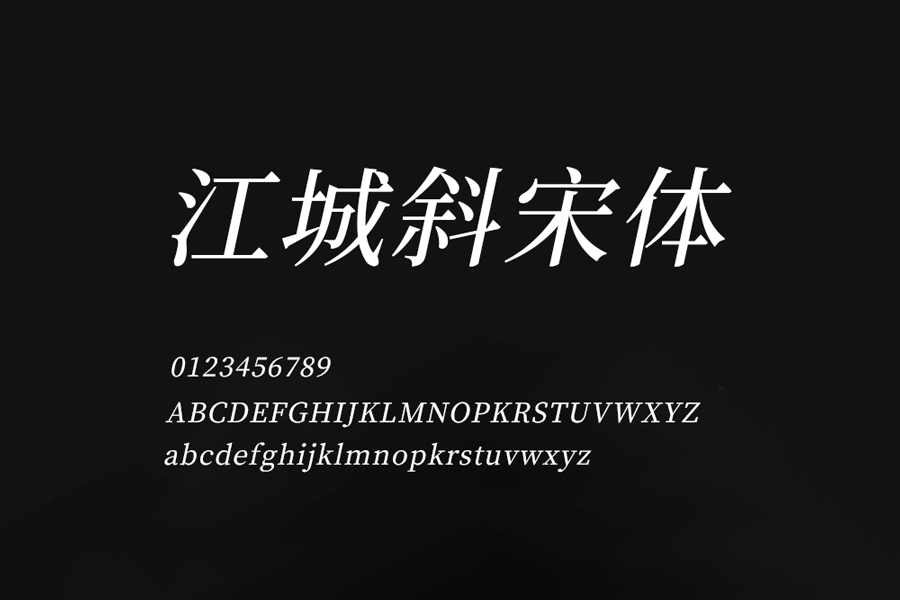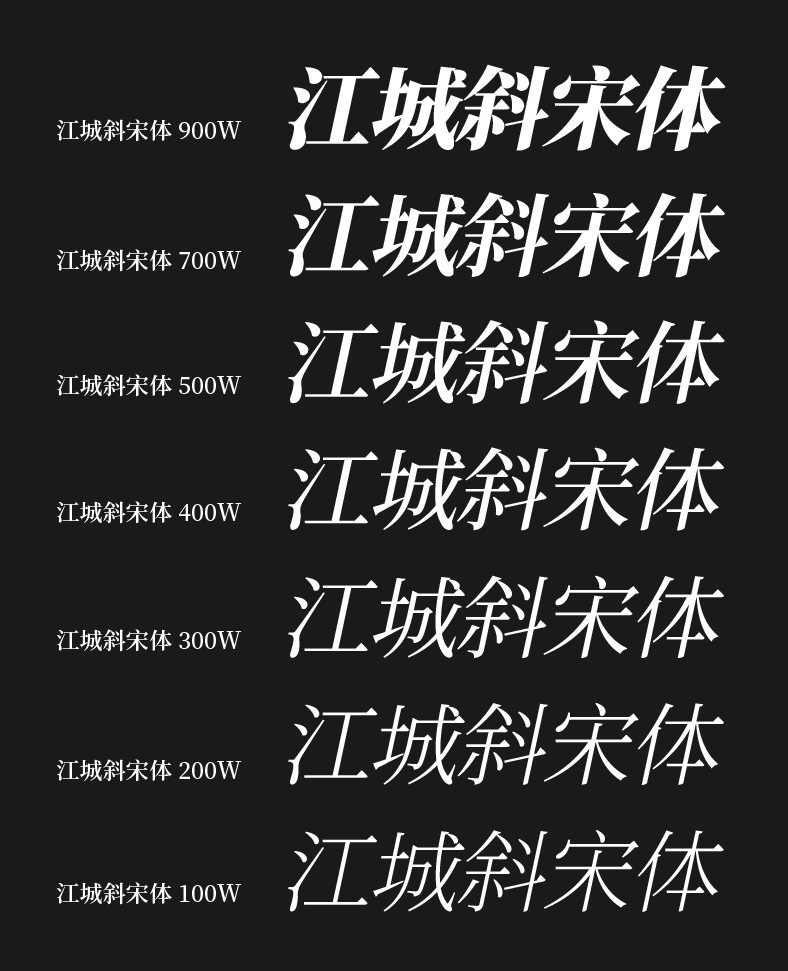
江城斜宋体是一款由设计师刘鹏基于思源宋体改造而成的免费可商用中文斜体字体。目的是为了解决部分软件(如 Keynote)无法正确倾斜中文字体的痛点。
字体在保留思源宋体横细竖粗、笔画末端衬线(装饰角)的基础上,将字形整体向右倾斜 12 度,使其更具视觉冲击力。同时,针对小字号下的撇捺交叉处做专门优化,避免出现粘连现象,保证了字体的可性。
江城斜宋体包含简体中文(GB2312)、繁体中文、日文、韩文、拉丁字母等字符集,覆盖从细到粗 7 个字重 (100W ~ 900W),可以满足正文、标题等多种排版需求。常常被应用在海报标题、品牌 LOGO 设计、广告包装、PPT设计等场景。